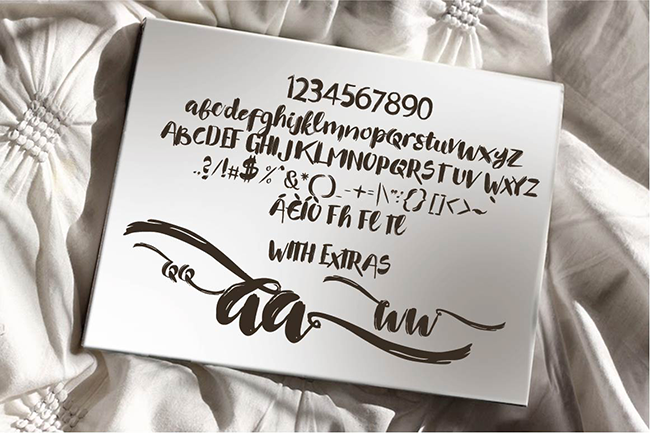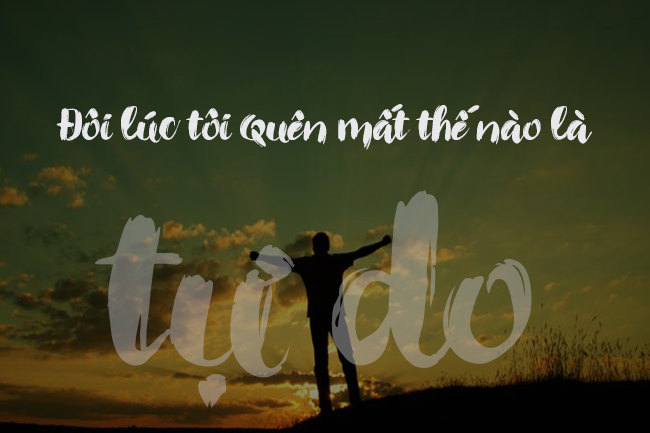
Wendi là một font script vẽ tay bằng cọ rất đẹp, đi kèm với một bộ ký tự trang trí bổ trợ. Phù hợp cao cho nhiều loại hình thiết kế truyền thông, thời trang và poster.